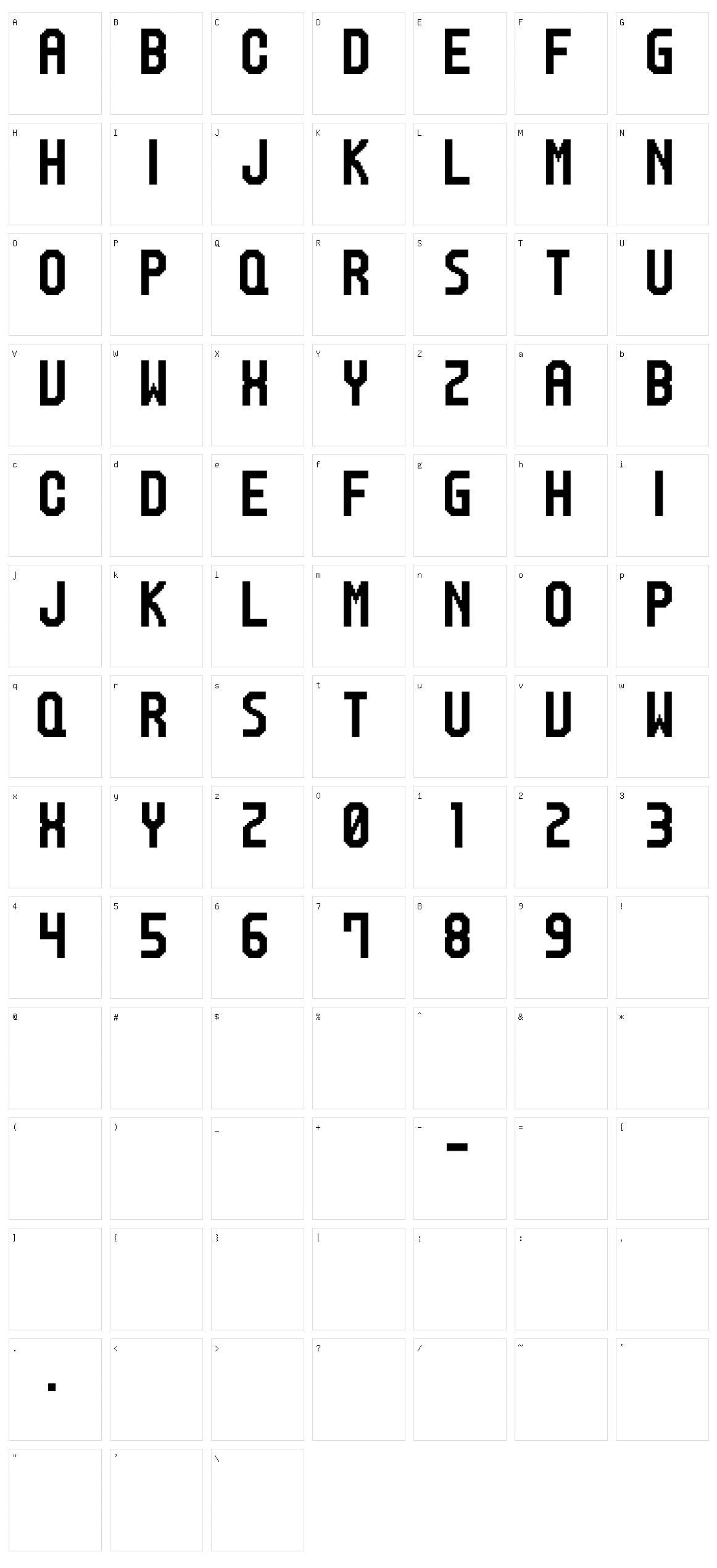
M20 SP-Ranker
Designed by: Miffies
ƒtƒ@ƒ~ƒRƒ“”ŁuƒXƒyƒ‰ƒ“ƒJ[vƒƒSƒtƒHƒ“ƒgB
u‚·‚®Ž€‚ÊŽålŒöv‚Å’´—L–¼‚ȁAŒ¾‚킸‚Æ’m‚ꂽ–¼ìiHjB
‚ ‚Ì“Á’¥“I‚ȃQ[ƒ€“à—e‚ƈقȂèA
ƒƒSŽ©‘̂͂¢‚½‚Á‚ăXƒ^ƒ“ƒ_[ƒh‚ȍì‚è‚Æ
‚È‚Á‚Ä‚¢‚½‚½‚߁A»ì‚ð‘Ø‚è–³‚­i‚߂邱‚Æ‚ªo—ˆ‚Ü‚µ‚½B
‚±‚̃tƒHƒ“ƒg‚ÅMiffiesƒtƒHƒ“ƒg‘æ20ì–Ú‚Å‚·B
‘‚­‚àA‚Æ‚¢‚¤‚©A‚悤‚â‚­A‚Æ‚¢‚¤‚©B
‘S‘RA‚Ü‚¾‚Ü‚¾‚È‚ñ‚Å‚·‚¯‚ǁB
¸i‚¹‚˂΁B